2023 年 18 种最佳日语字体(免费和付费)
已发表: 2023-05-17你有没有想过如何用独特的日本文化来提升你的设计项目? 或者,也许您正在寻找有关在下一个项目中使用的最佳字体的灵感。 好吧,别再看了,因为我们已经为您提供了 18 种最佳日文字体列表。
在本文中,我们将探索日文印刷术的世界,并展示当前可用的最令人惊叹、最实用和最流行的字体。
我们的列表包括各种样式,从传统书法到现代无衬线字体。 此外,我们将为您提供一些您以前可能不知道的关于日文字体的有趣事实。
无论您是平面设计师还是喜欢尝试不同字体的人,本文都适合您。
所以,系好安全带,准备好让自己沉浸在迷人的日文排版世界中,我们将带您了解 18 种最佳日文字体。
最佳高级日语字体
Best Premium Japanese Fonts 是为您的设计增添一丝优雅和精致的好方法。 看看我们在下面精心挑选的选择,将您的项目提升到一个新的水平。
日本版
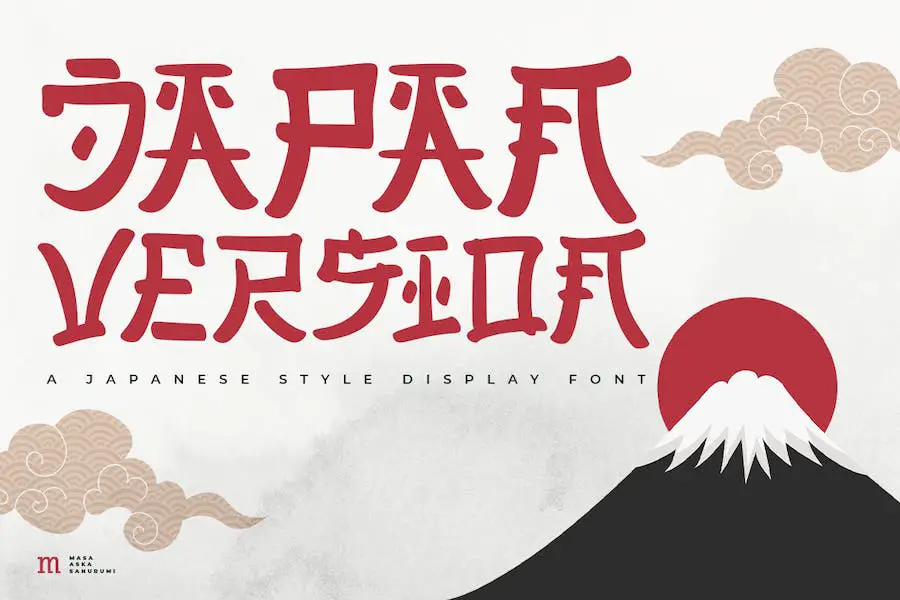
Japan Version 是一种显示字体,可以很好地添加到您的收藏中。 它具有日式风格,可以为您的设计项目增添趣味。 无论您是创建社交媒体帖子、引述、图像叠加层、海报、打印需求、网站横幅还是其他任何内容,此字体都适合您的所有设计需求。
日文版的突出特点之一是其独特的日式字形,使与它一起使用的任何文本都具有独特的感觉。 此外,这种字体易于阅读,并具有从细到粗的各种粗细和样式,使您的设计具有多功能性。
此外,这种字体非常适合那些希望创建大量排版设计的人,因为它提供了广泛的字符,包括平假名、片假名和汉字。 使用日本版,您可以创建精美且引人入胜的视觉效果,以吸引观众的注意力。
日本瑞奇
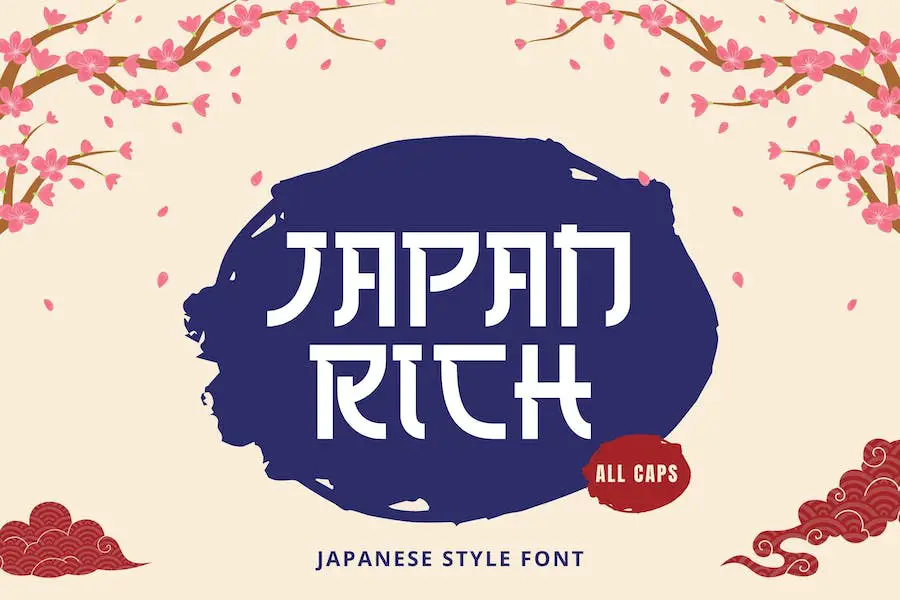
Japan Rich 是一种新的字体产品,从日本汉字排版中汲取灵感。 它非常适合想要为其项目增添额外优雅和精致感的平面设计师。
Japan Rich 的突出特点之一是它的多功能性——它可以用于各种设计环境,包括徽标和品牌、社交媒体帖子、广告和产品设计。 Japan Rich 凭借其大胆而现代的美学,保证让您的设计脱颖而出。
这种字体的另一个主要卖点是它对细节的关注。 每个字符都经过精心设计,以反映传统日本书法字体的美丽和复杂。 这使得 Japan Rich 成为任何希望将日本文化元素融入其作品的设计师的绝佳选择。
日本人
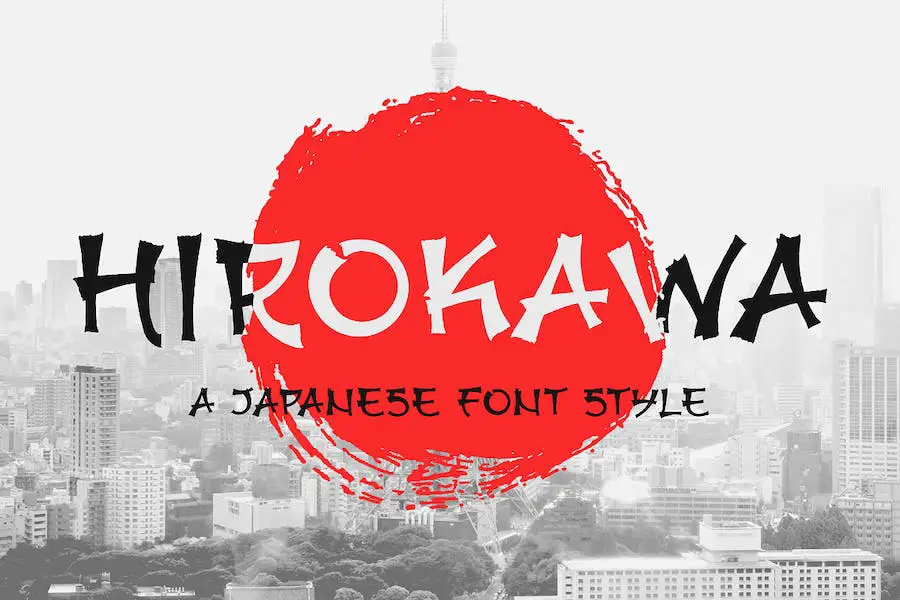
日本字体是一种现代而酷炫的字体,体现了日本文化之美。 其复杂的设计和手工制作的细节使其非常适合用于网站、社交媒体、演示文稿、印刷材料等各种项目。
对于希望在作品中增添一丝日本风情的平面设计师来说,这款字体是必备之选。 它以大胆和圆滑线条的独特组合为特色,使其适用于现代和传统设计。 它的多功能性也使其非常适合各种项目。
日本字体非常适合那些想要用他们的设计发表声明的人。 它有一个明显的酷因素,可以将您的项目提升到一个新的水平。 凭借其引人注目的外观,您可以肯定它会吸引任何看到它的人的注意力。
卫物
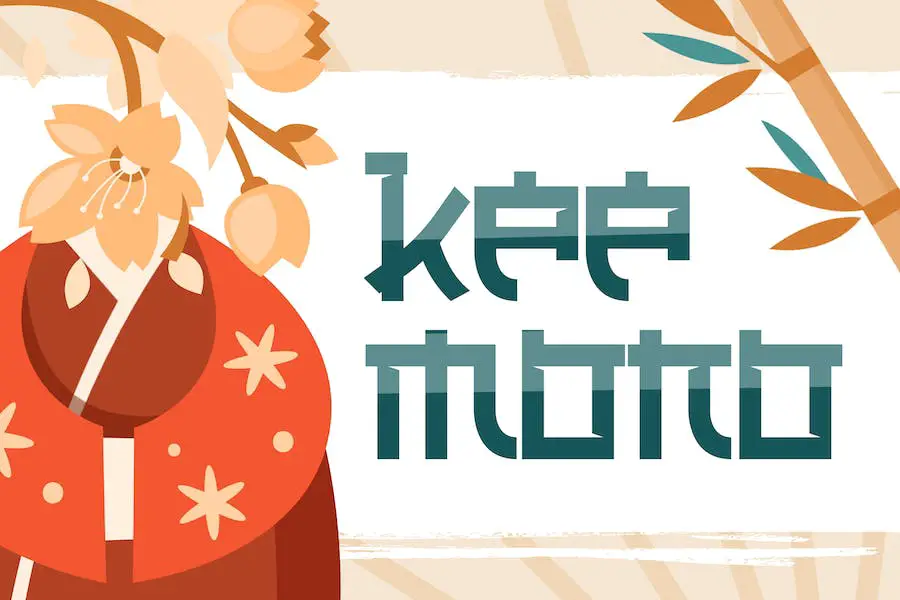
Keemono 是一款令人惊叹的显示字体,捕捉了日本文化的真正精髓。 其独特的书法和复杂的字符非常适合为任何设计项目增添真实感,从与日本相关的文章到社交媒体页面封面。
凭借其优雅精致的设计,Keemono 将把观众直接带到日本的中心。 该字体的迷人魅力非常适合亚洲主题游戏、日本文化活动海报、YouTube 封面,甚至是 YouTube 缩略图。
Keemono 拥有一系列完美体现日本文化之美的角色,一定会给观看它的人留下深刻印象。 其复杂的细节和简洁的线条使其成为任何字体库的必备补充。
日本天皇
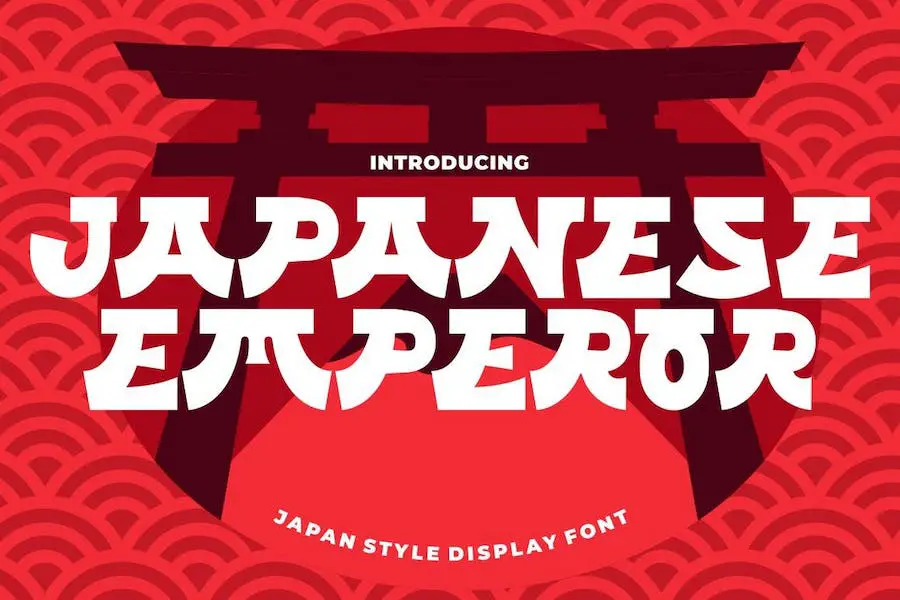
Japanese Emperor 是一种从日本风格中汲取灵感并创建准确反映日语的字符的字体。 该字体的设计经过量身定制,使读者能够快速轻松地阅读文本,使其适用于所有类型的媒体。
Japanese Emperor 字体可以提升您项目的整体美感,无论是徽标、婚礼请柬、品牌、着陆页、海报、标题、贺卡、邀请卡、社交媒体帖子、工艺品、报价单,还是任何其他创意项目。
总之,如果您正在为您的 Circuit 项目寻找一种日文字体,那么 Japanese Emperor 是一个很好的选择。 凭借其真实的日文字符和跨各种媒体的多功能性,这款字体一定能满足您的所有设计需求,让您的项目脱颖而出。
三崎
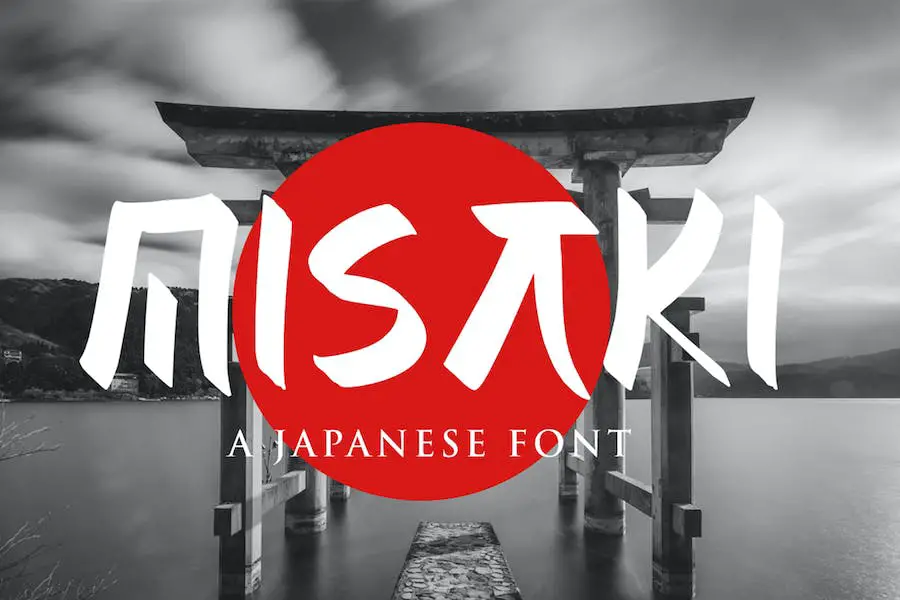
Misaki 是一种梦幻般的日本风格显示字体,可以使任何设计脱颖而出。 它的可读性极佳,将为您的印刷作品或餐厅品牌增添引人注目的元素。 有了 Misaki 的功能,您就不会出错!
这种字体非常适合那些为 Word 寻找简单而优雅的日语字体的人。 在设计日本主题项目时,Misaki 将很快成为您最喜欢的首选字体。 它具有干净、时尚的外观,可为您的设计增添专业气息。
Misaki 最好的地方之一就是它的多功能性。 它适用于任何设计风格,无论是现代的还是传统的。 这种字体还具有出色的易读性,即使是小字体也很容易阅读。 它非常适合创建需要大量文本元素的设计。
最后的手里剑
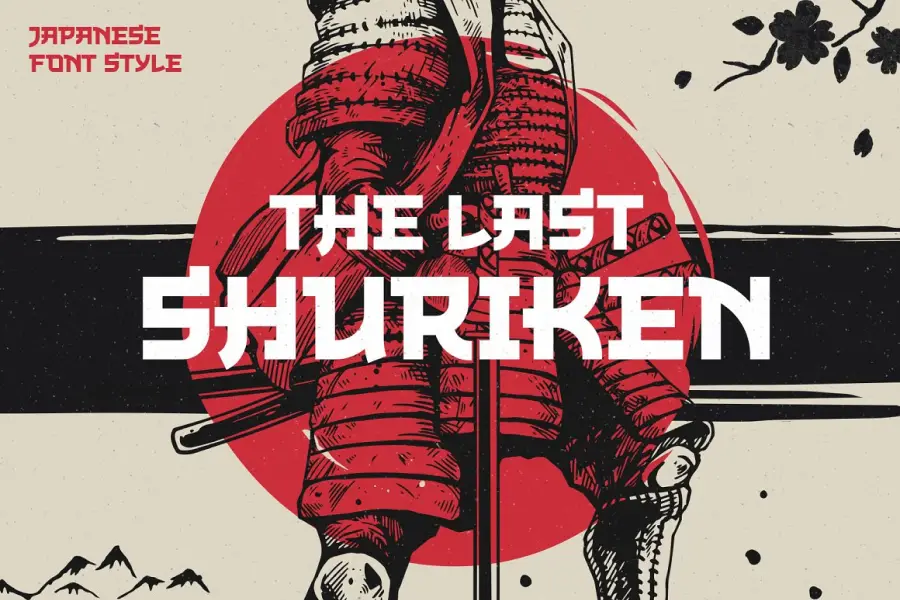
The Last Shuriken 是一种大胆而时尚的日本字体,从现代日本食品品牌和动漫名称中汲取灵感。 这是一款全大写字体,具有统一的大写高度和独特的形状,非常适合展示用途。
这种字体适用于各种设计项目,如日本食品主题设计、标志、标题、海报、引语、电影、游戏和服装。 凭借其风格替代和 PUA 编码,The Last Shuriken 还支持多种语言,使其成为一个多功能的字体选项。
总的来说,The Last Shuriken 是那些寻求在他们的设计项目中添加现代日本风格的人的绝佳选择。 其强烈的笔触和独特的形状使它成为一种引人注目的字体,一定会吸引任何观众的眼球。
杰伦
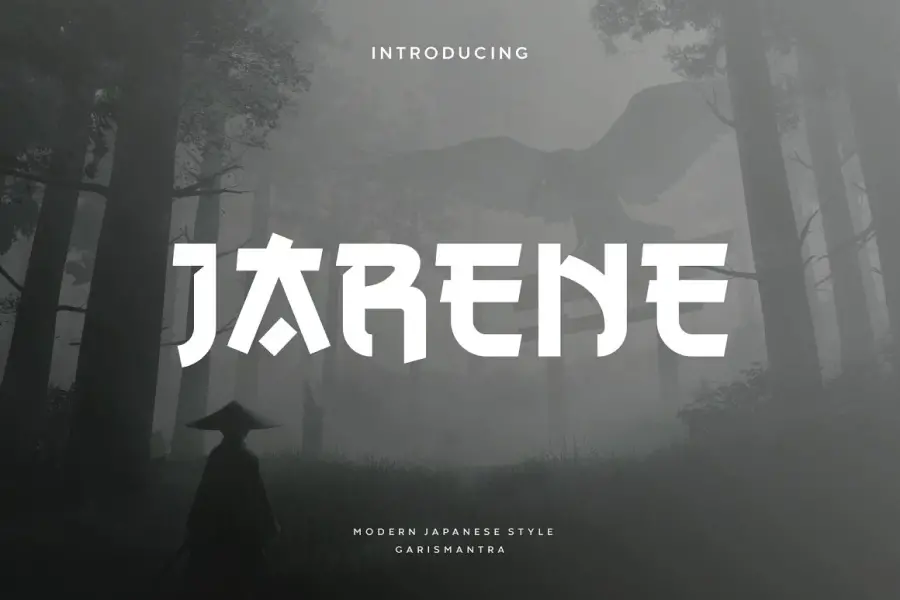
Jarene 是一种受日本启发的字体,将传统汉字字符与现代英语设计相结合。 该字体的独特风格融合了直线和曲线,营造出让人联想到忍者形象的专业外观。
它可以用于各种设置,包括日本或动漫设计项目,以及品牌推广活动。
Jarene 因其动态的形状和时尚的外观而成为一种杰出的字体。 直线和曲线的结合使它比其他字体更有优势,使其既多才多艺又具有视觉吸引力。 它融合了传统的日本元素和现代英语设计,使这种字体成为那些寻求与众不同的人的绝佳选择。
藤丸
Fujimaru 是一款强烈推荐给那些寻求具有亚洲和东方风格的大胆手工毛笔字体的人的字体。 这种字体非常适合具有亚洲特色的创意项目,例如恐怖效果或卡通有趣的标题。
Fujimaru 字体用途广泛,可用于各种设计应用,例如标题、电影海报、引述文本等。 其独特的笔触赋予它一种有机的感觉,使其从市场上的其他日本笔刷字体中脱颖而出。
Fujimaru 的大胆和手工制作的外观使其成为希望为其作品增添个性的设计师的绝佳选择。 此外,它的多功能性使其可以在不同的环境中使用,这对于想要为各种项目创建独特设计的设计师来说是一笔宝贵的投资。
卡塔纳
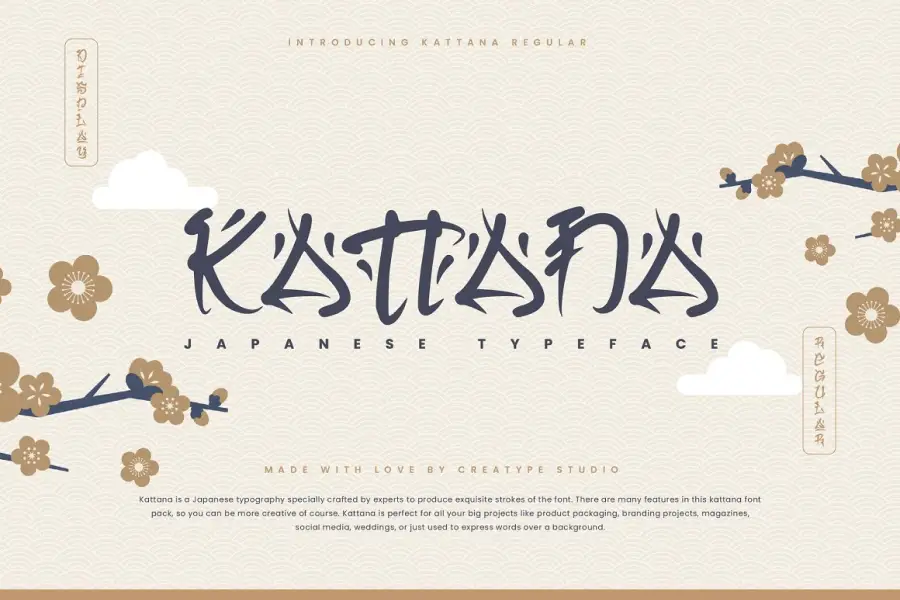
Kattana 是一款日文排版字体包,由专家精心制作,可产生精美的字体笔触。 这个字体包提供了许多创意功能,让设计师在他们的项目中更具创新性。
Kattana 非常适合各种项目,例如产品包装、品牌、杂志、社交媒体、婚礼,或仅用于在背景上表达文字。
如果你正在为 Canva 寻找日语字体,Kattana 是一个很好的选择。 其精美的书法将为您的项目带来独特而难忘的外观。 该字体易于使用,可以帮助您将设计提升到一个新的水平。 总的来说,Kattana 对于任何正在寻找可以使他们的项目脱颖而出的高质量日文字体包的人来说都是一笔巨大的投资。
UNGAI
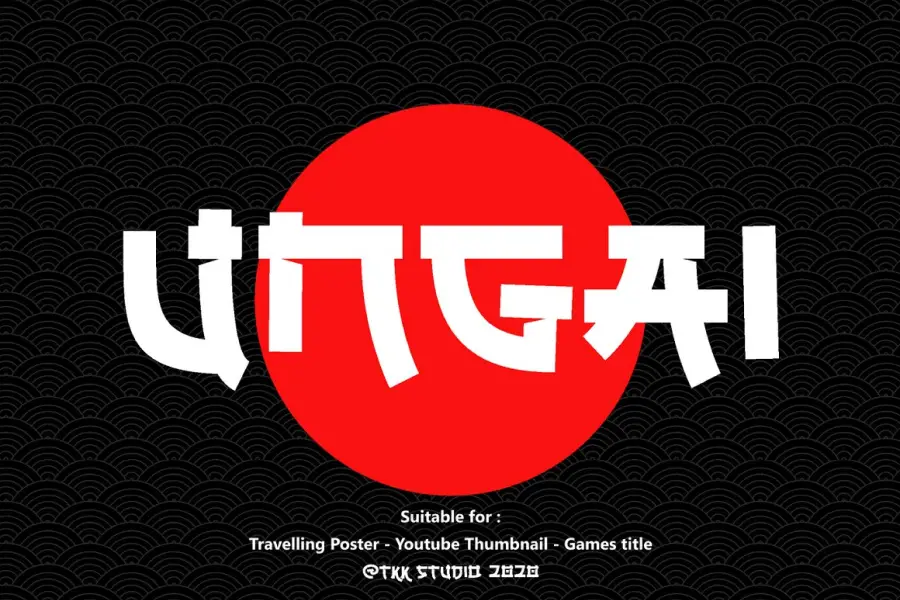
Ungai Japanese 字体是一种现代且充满活力的字体,非常适合各种设计项目。 该字体的灵感来自片假名形状,在内部连接处被切掉,以营造出快速而完整的动作外观。
这使其非常适合用于在线游戏、海报、电影标题、快餐菜单、杂志、YouTube 封面、缩略图和社交媒体页面封面。
Ungai 字体的另一大特点是它的灵活性。 该字体被设计为适用于不同的大小,使其成为各种设计项目的理想选择。 无论您是创建大型海报还是小型缩略图,该字体都将保持其清晰易读。
冲床
Okidoki 是一种会让你微笑的字体! 对于想要为他们的设计项目增添一些可爱和乐趣的人来说,这是完美的选择。 这种字体最好的地方之一是您无需切换键盘语言即可使用它。 您需要做的就是用平假名或片假名书写,然后您就可以创建一些很酷的卡哇伊图形了。
凭借其活泼俏皮的外观,如果您正在寻找能够吸引人们注意力的东西,Okidoki 是一个绝佳的选择。 该字体旨在易于阅读,适用于各种项目,包括海报、传单、邀请函等。
最好的免费日语字体
如果您希望为您的设计项目添加一些独特的风格,请务必查看我们的最佳免费日文字体列表。 您不会想错过这些可以将您的设计提升到一个新水平的首选。
几乎日本卡通
Almost Japanese Cartoon 是一种可以免费用于个人项目的字体。 但是,如果您计划将其用于商业目的,则需要通过 PayPal 捐赠购买商业字体最终用户许可。
这种字体的风格受到日本卡通和漫画的启发,让您的项目带有东方风情。 它的独特功能包括粗体和粗笔画,非常适合强调文本的特定部分。 此外,该字体的俏皮设计有助于为您的项目增添个性和魅力。
如果您正在寻找用于纹身设计的日语字体,Almost Japanese Cartoon 可能是一个很好的选择。 该字体独特的风格使其脱颖而出,其粗笔画有助于确保您的纹身即使随着时间的推移也能保持清晰可辨。
几乎日本光滑
Almost Japanese Smooth 是由 Galdino Otten 设计的一款出色的 3D 显示字体。 这种字体具有迷人的流畅性和独特的风格,可以增强任何设计项目。
这种字体的一大特点是它与 Figma 的兼容性,这使其成为寻找高质量日文字体以用于其 Figma 项目的平面设计师的绝佳选择。
Almost Japanese Smooth 字体具有圆润的外观,使其具有三维外观。 该字体的光滑边缘营造出一种抛光和精致的外观,适合各种设计风格。
日本人
日本字体是一种美丽可爱的字体,为您的设计项目增添了精致的触感。 其独特的风格和优雅的曲线使其在市场上的其他字体中脱颖而出。 这种字体非常适合想要在设计中添加日本文化气息的平面设计师。
日本字体具有几个令人兴奋的功能,使其对设计师很有吸引力。 它的字符范围很广,包括平假名、片假名和汉字,适用于不同类型的设计项目。 此外,该字体具有平滑和干净的纹理,增强了易读性,即使在小尺寸下也易于阅读。
日本人孔
Kong Japanese 是一款制作精良的显示字体,散发着迷人优雅的气息。 这种令人愉悦的手写字体是从独特的日文汉字字体中汲取灵感而创建的,这使得它从其他字体中脱颖而出。
Kong Japanese 的有机笔触和曲线无缝融合在一起,创造出具有视觉冲击力和凝聚力的成品。 它的多功能性使其非常适合用于徽标、贺卡、海报、书籍封面和更多设计项目。
如果您正在搜索 Google 日语字体,那么 Kong Japanese 就是您的最佳选择。 它是一种兼具风格和实质的顶级字体。 该字体结合了优雅、优雅和独特性,肯定会受到任何人的欢迎。
经常问的问题
日本字体是一种排版风格,其中包含来自日本书写系统的字符。 它们可用于为设计项目添加独特的触感或传达特定的文化审美。
使用日文字体可以为您的设计项目增添视觉趣味,并有助于传达特定的文化审美。 此外,它们可以成为在拥挤的设计环境中脱颖而出并让您的工作更令人难忘的好方法。
结论
总之,日文字体是为您的设计项目添加创意和独特元素的好方法。 在本文中,我们讨论了 18 种最好的日文字体,您可以在设计中使用它们来使它们脱颖而出。